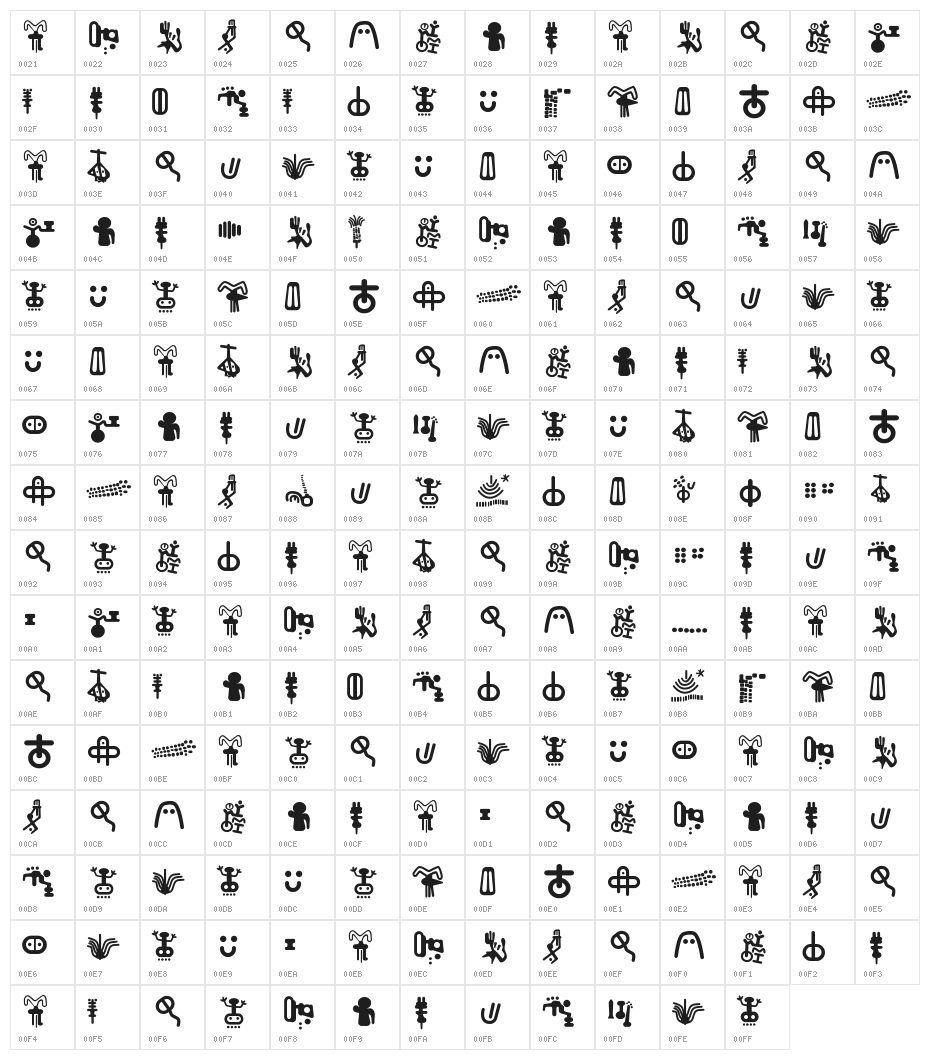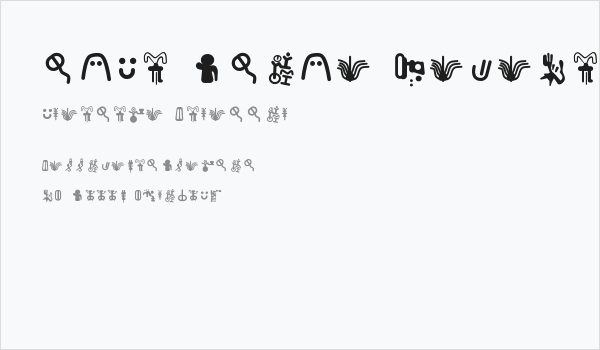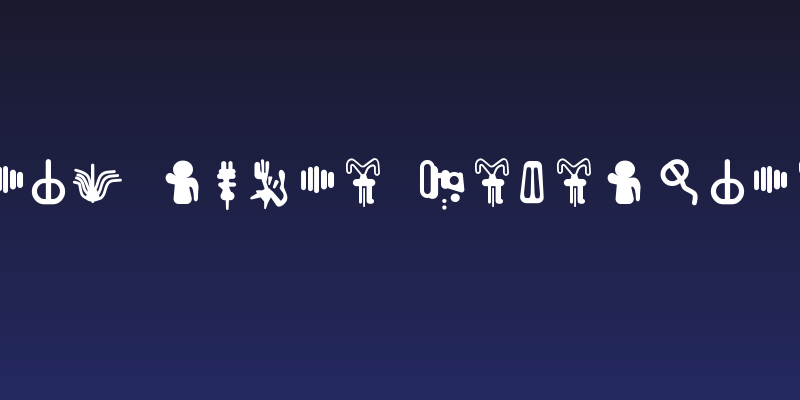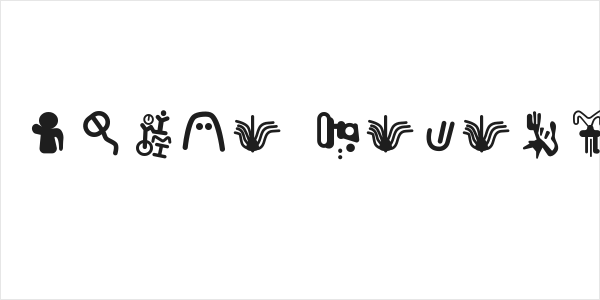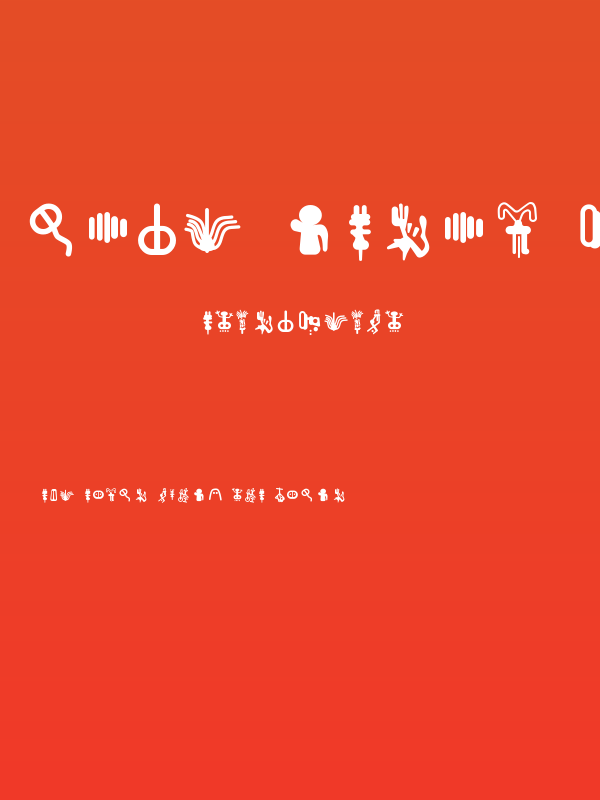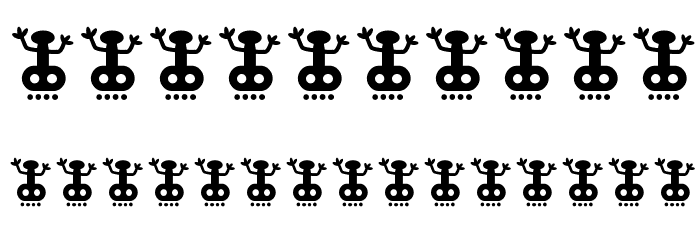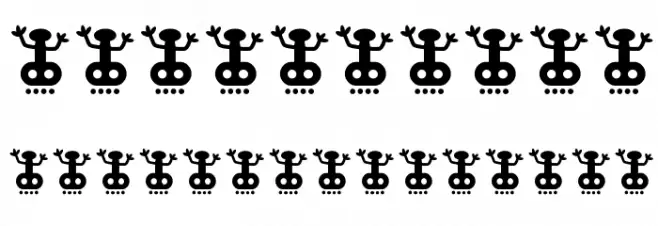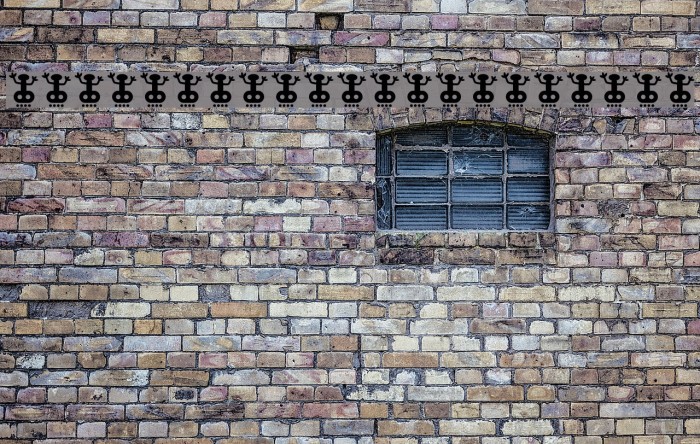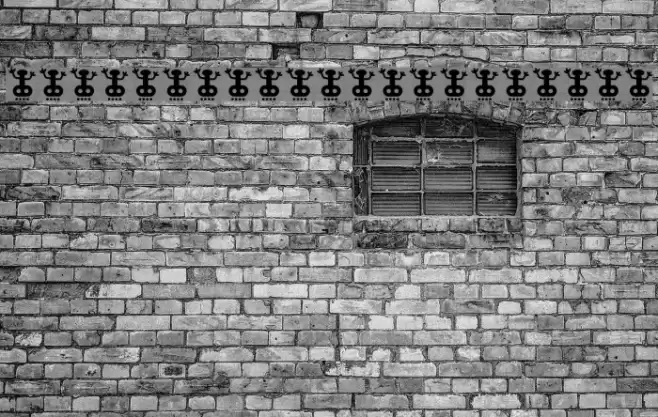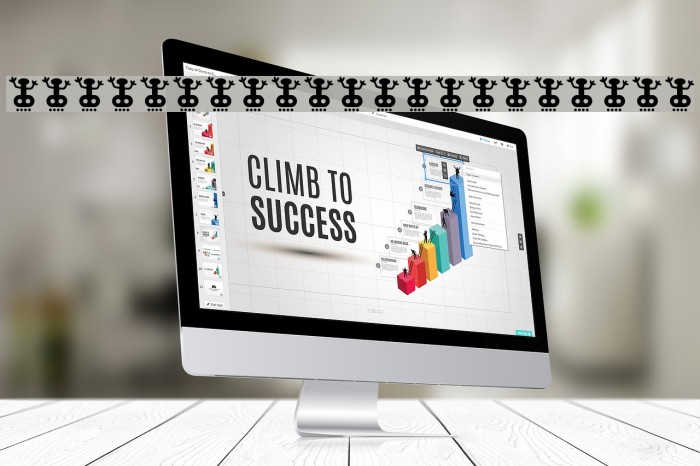
Inga Stone Redesigned Font
| Style général | Primitive, Symbolic, Decorative |
| Cas d'utilisation | Logos, Posters, Artistic projects, Themed branding |
| Projets proposés | Cultural exhibitions, educational materials, themed posters, branding for historical or archaeological projects, artistic installations. |